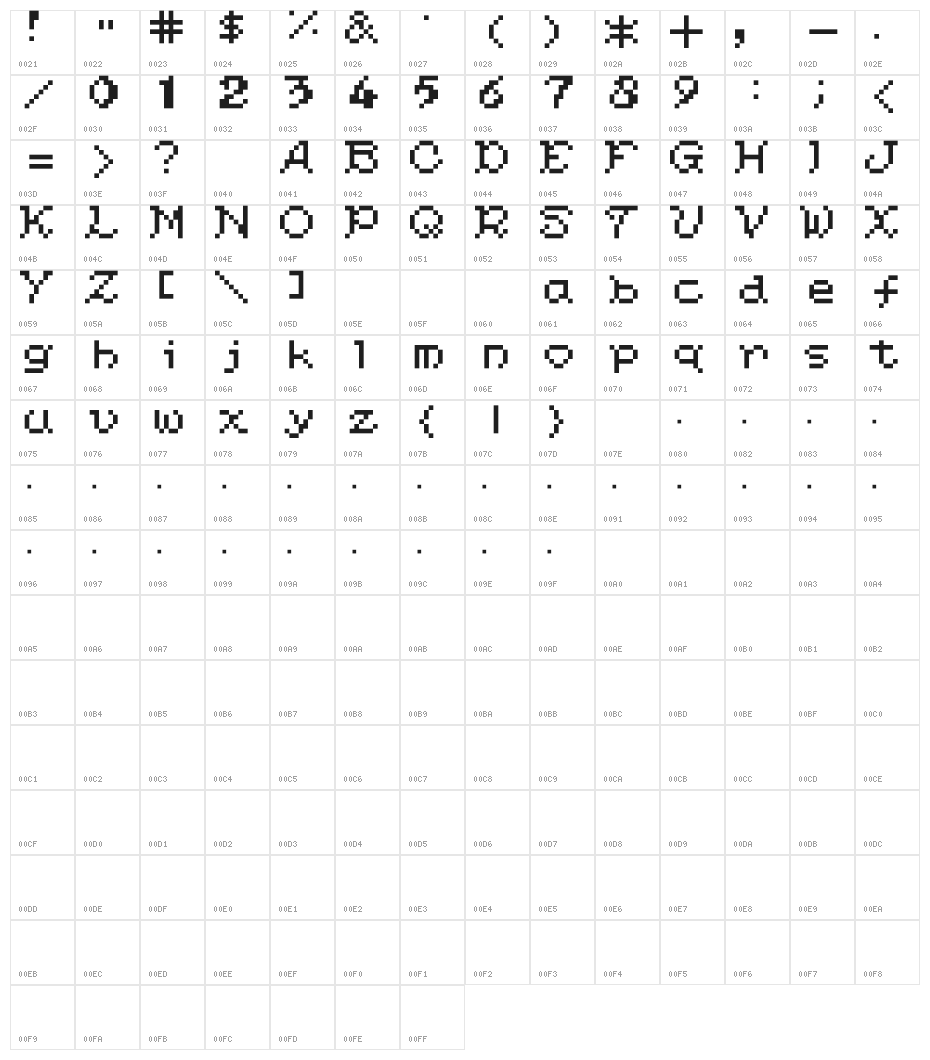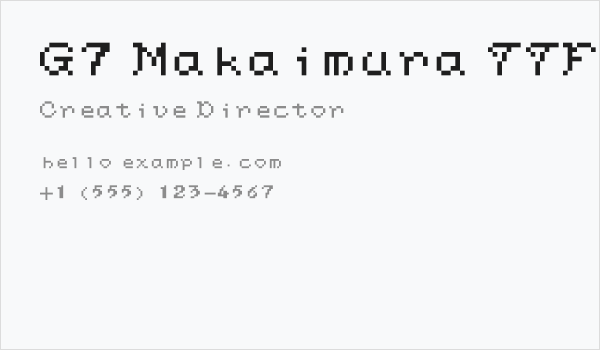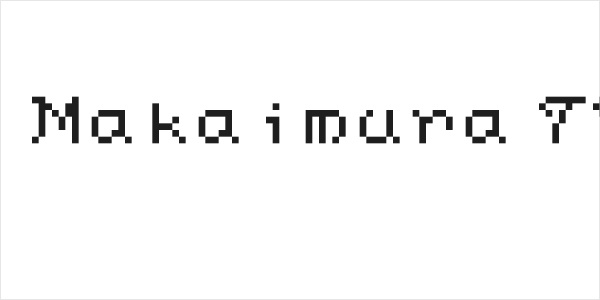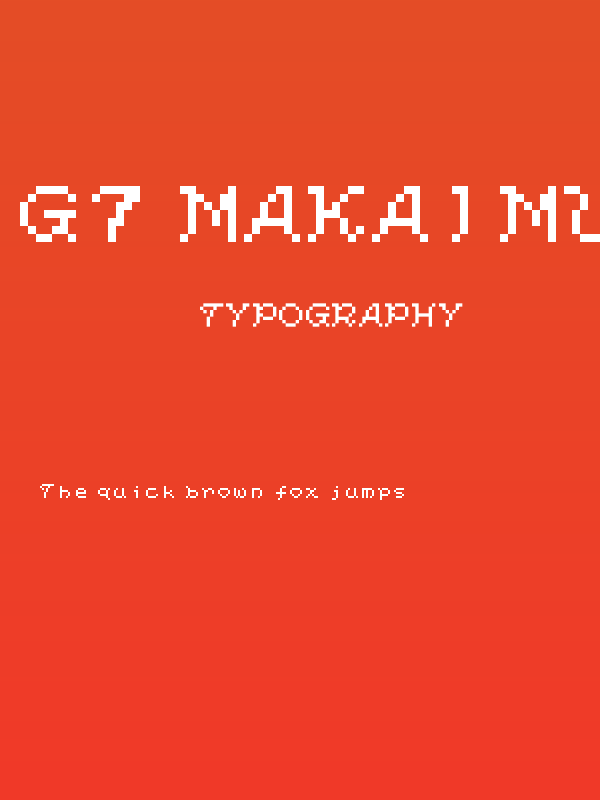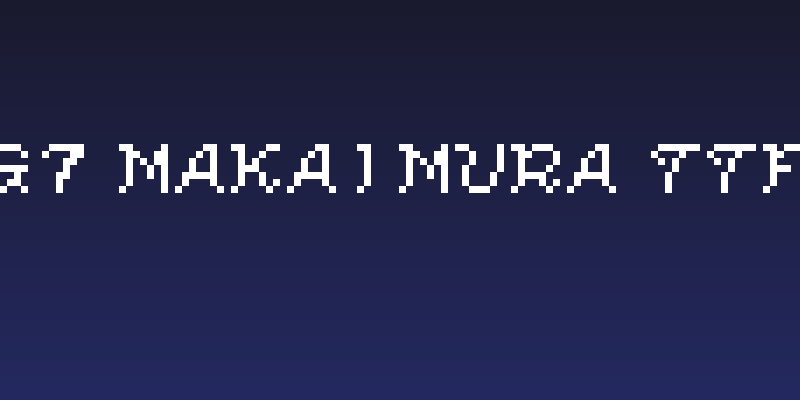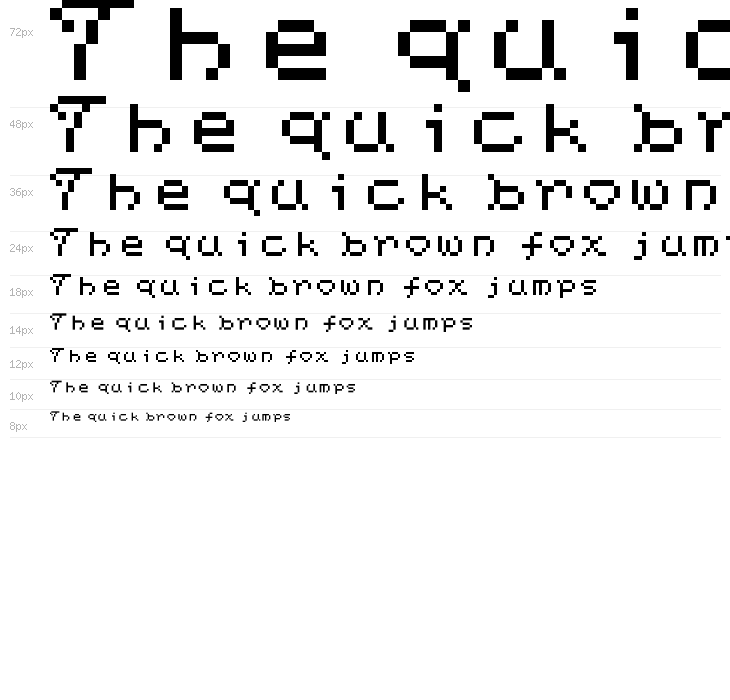
G7 Makaimura TTF Font
✎ Pixel
| Caso d'uso | Logos, Headlines, Digital Art |
| Progetti proposti | Ideal for retro video game designs, digital art projects, nostalgic branding, and any creative work that seeks to evoke a classic gaming feel. |